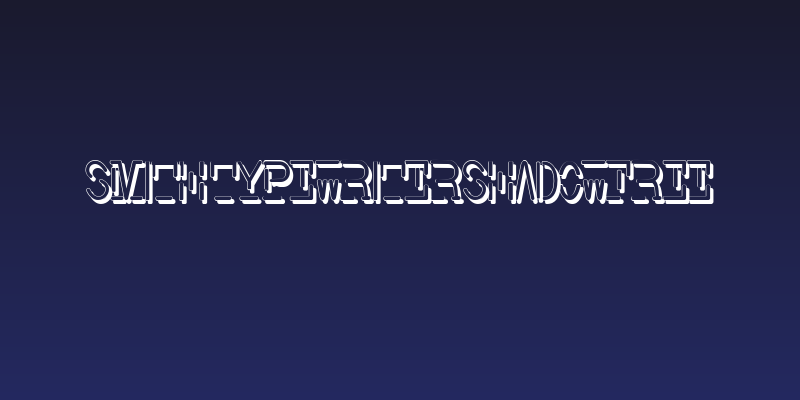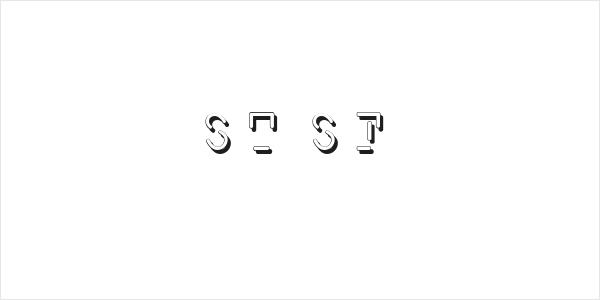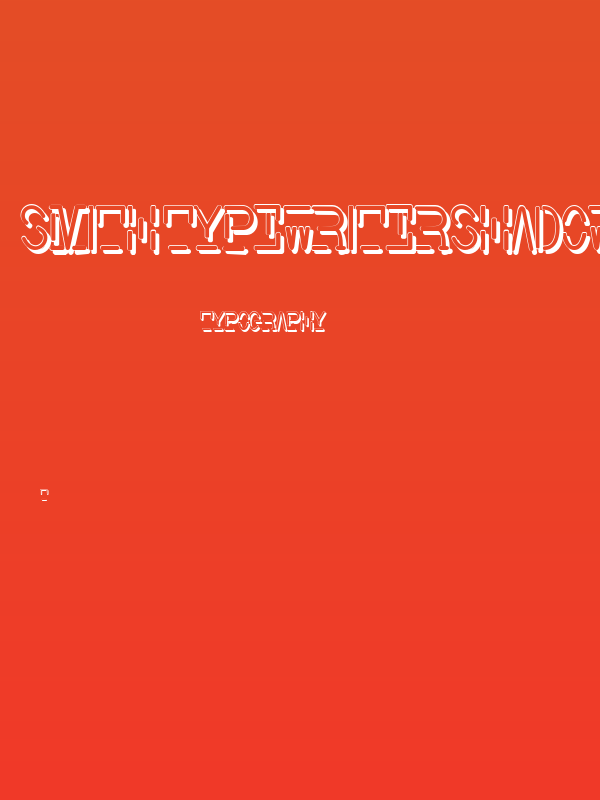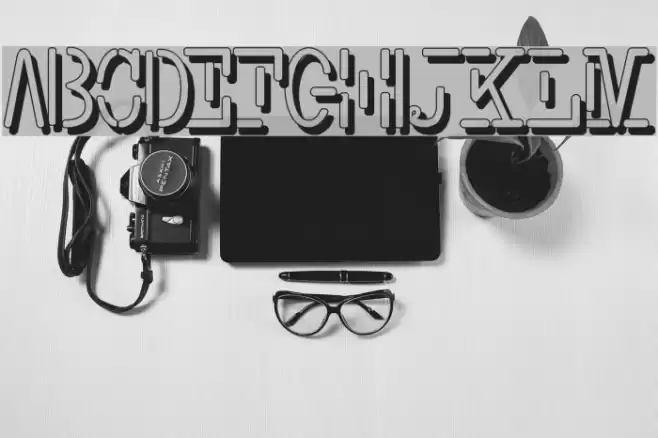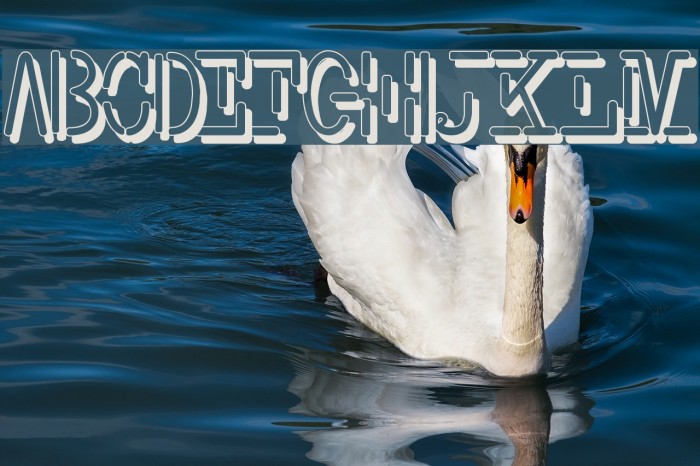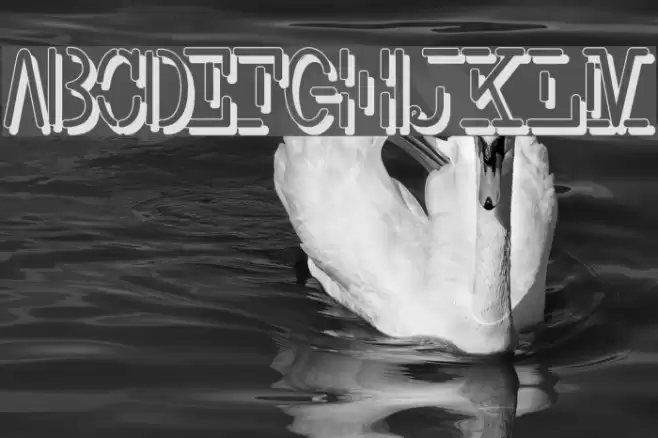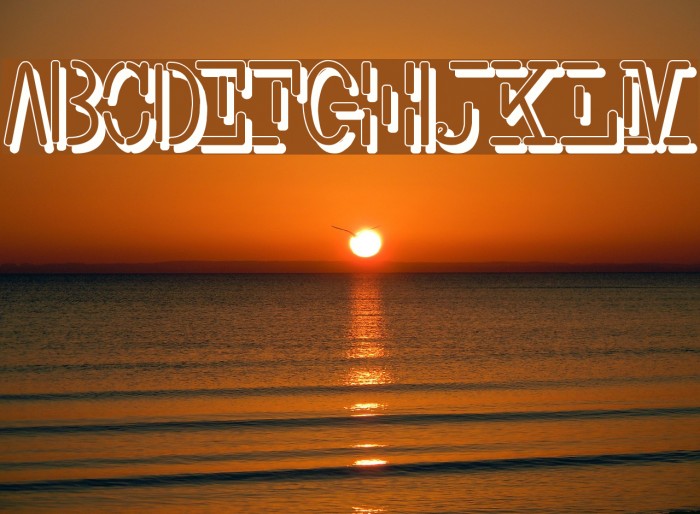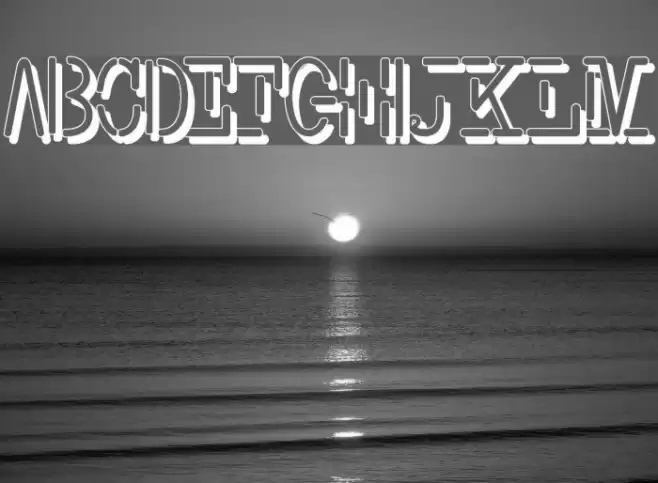
Smith-TypewriterShadowFree Font
✎ Typewriter
| Estilo general | Vintage |
| Caso de uso | Headlines, Posters, Branding |
| Proyectos propuestos | Ideal for retro-themed posters, branding, and eye-catching headlines. |